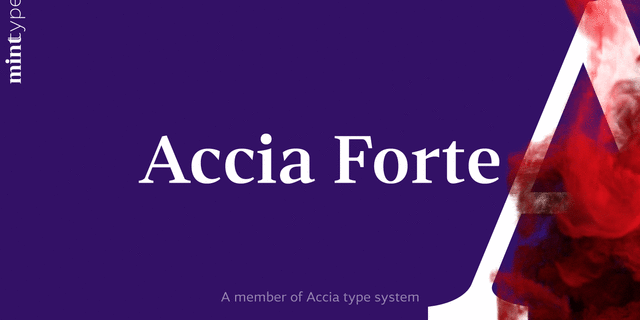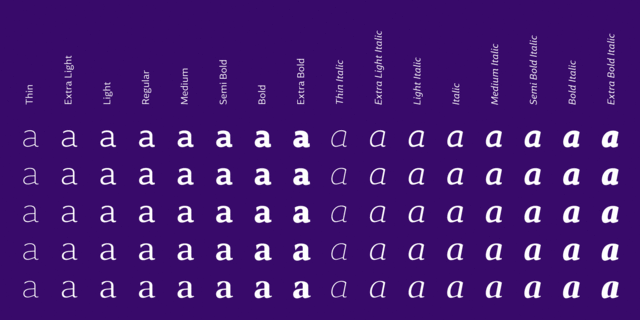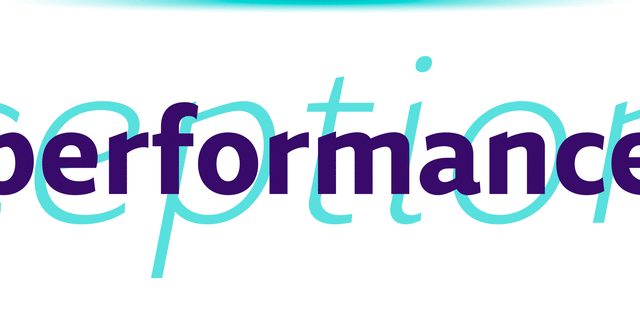
Accia Variable (2 шрифта)
Accia – один из первых в мире шрифтов с вариативным переходом от гротеска к антикве. Диапазон значений оси жирности – от Thin до Extra Bold, а по оси засечек – от Sans до Forte. Accia спроектирована так, чтобы ее можно было использовать в любой точке пространства дизайна, а ее различные варианты прекрасно работают вместе как бесконечно гибкая типографическая система. Гарнитура содержит 879 глифов, поддерживающих несколько языков на основе латиницы и кириллицы, вместе с дополнительными наборами цифр и знаков препинания, капителью, лигатурами и другими распространенными функциями OpenType. Accia также доступна в виде 5 отдельных шрифтовых семейств: Accia Sans, Accia Flare, Accia Piano, Accia Moderato и Accia Forte. Гарнитуру разработал Андрей Константинов в студии Mint Type в 2021 году.